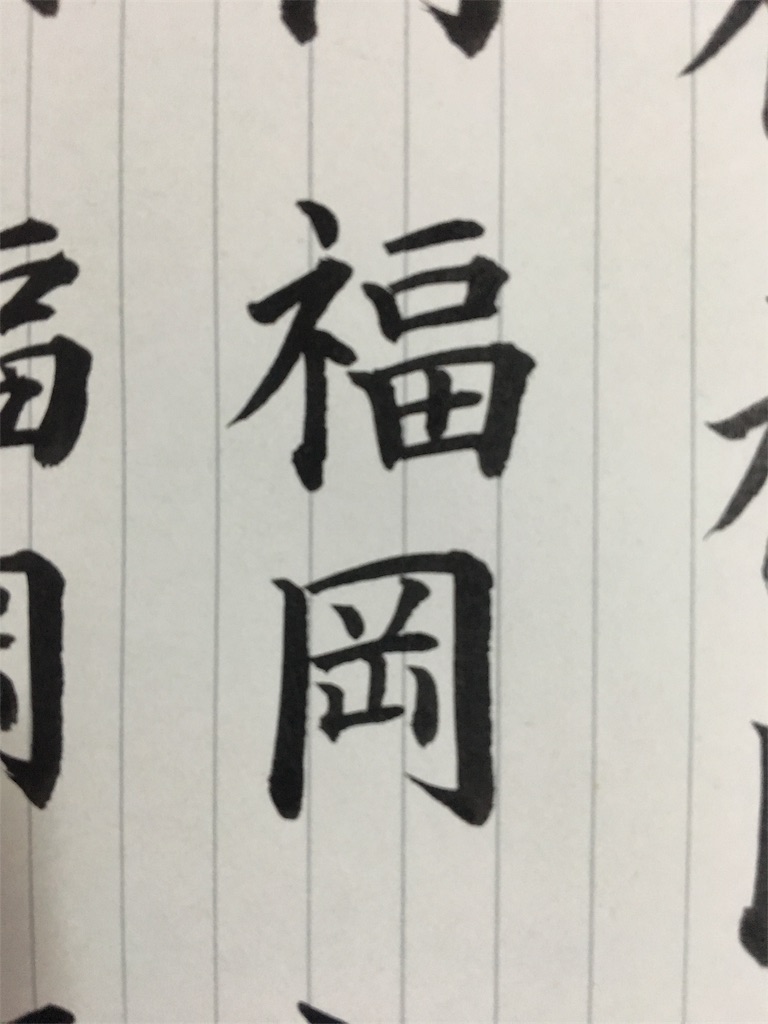
先ほど、インスタグラムに
福岡
という字を投稿しました。
都道府県名シリーズ、
何回も練習して、まぁ良いかな。
というものを投稿しているのですが…
最初の方はこんな感じに書いていました。
何か腑に落ちない…
と思って字典を引きました。
がっかりさせてしまったらごめんなさい!
字書、バリバリ使っています。
正しく書けているか、の確認の為です。
皆さんに嘘を教える訳にもいかないので、
ブログに載せている字は全て
納得するまで練習してから載せています。
これも実力の無さゆえ、ですが…
頭で分かっていても、
なかなか自分の思うように書けないのが現実です。泣
さて、福岡 の字に戻って…
福 という字の
へん と つくり の間。
インスタに載せたものと比べると、空間が狭いのがお分かりいただけるでしょうか?
字典を引いて気づきました。
ふところが狭くて、何だか息苦しい。
と、いうことで、へん と つくり の間を
スッと一本線が通るように空間を作る。
でも間のびしないように…
コレがなかなか難しい!
ちょっと爽やかになったかな?
というところで、インスタに掲載したのが
1枚目の画像です。
私自身も、爽やかで懐の広い人になりたいものです
(*゚▽゚*)
まずは字から、意識して。
ふところの広さ、大切です♡